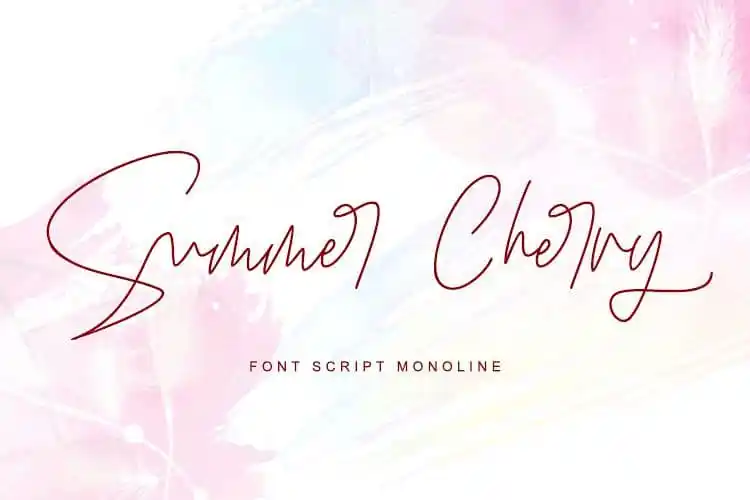
Summer Cherry Script Font
Esta é uma fonte script que oferece um toque natural à sua próxima criação criativa. Introduzimos Summer Cherry Script, uma font cuidadosamente projetada e compartilhada por a designer letterara. Este estilo monolineado é perfeito para criar logotipos belíscios, design elegante de embalagens sofisticadas, materiais de wedding stationery, websites e qualquer outro projeto que requer um toque autêntico e luxuoso. Especialmente versátil, Summer Cherry Script inclui uma ampla gama de swashes (da a até z) e alternativas (A até Z, a até z), permitindo-lhe criar um visual único e personalizado ao seu logotipo ou nome. Esse toque autêntico e elegante irá deixar sua marca distintiva, mesmo sob qualquer situação. Seja você criando um logo para uma empresa em ascensão, uma marca de luxo sofisticada, um material de casamento exuberante, ou um site requintado, Summer Cherry Script é perfeito. Seu estilo natural e toque elegante garantirão que seu design seja irresistível e imediatamente reconhecível. Não hesite em adicionar este recurso gráfico à sua próxima ideia visual!